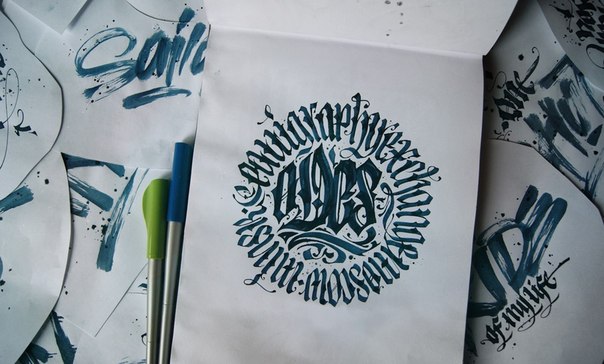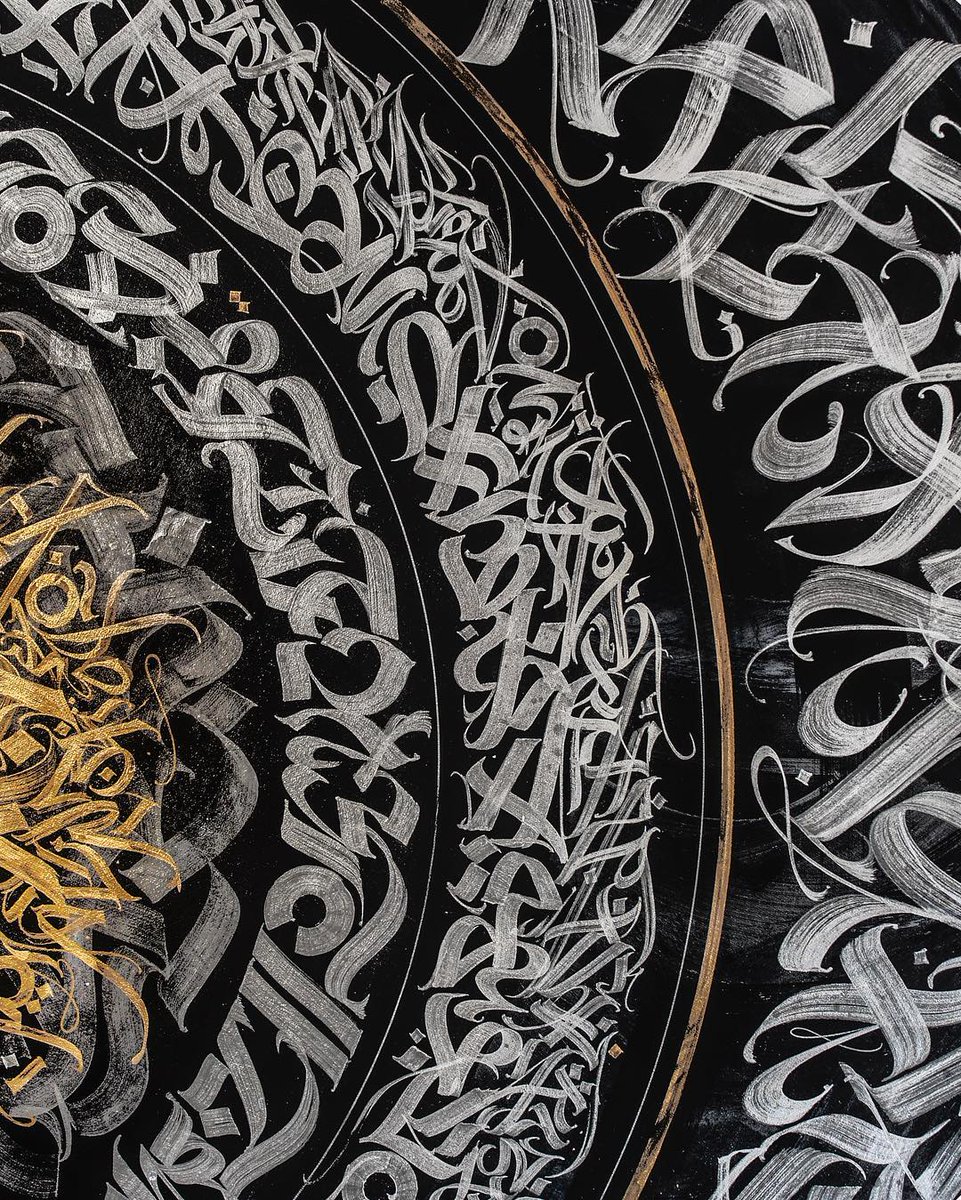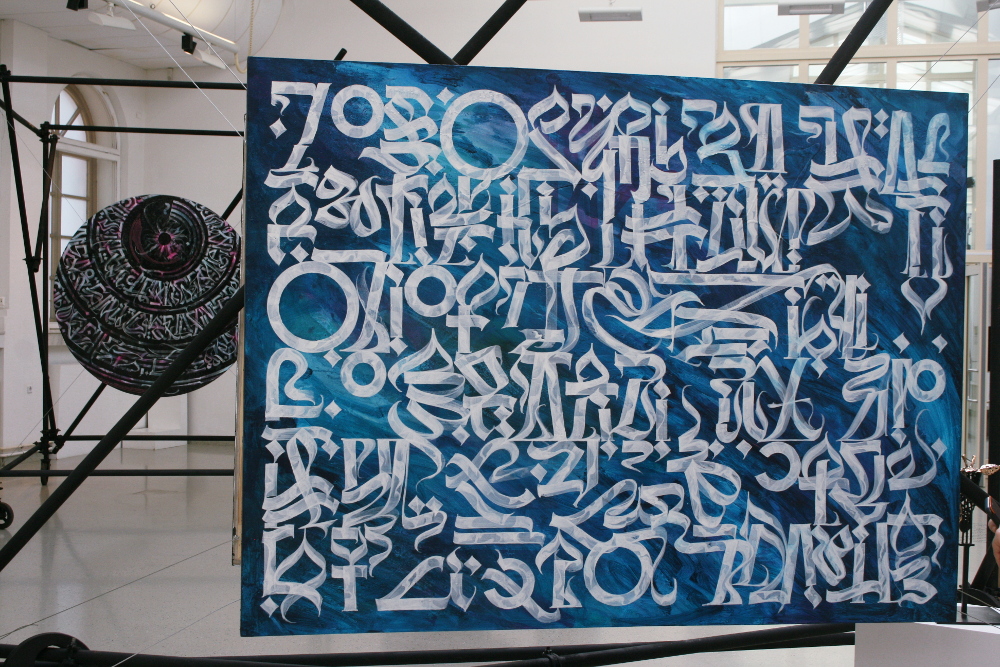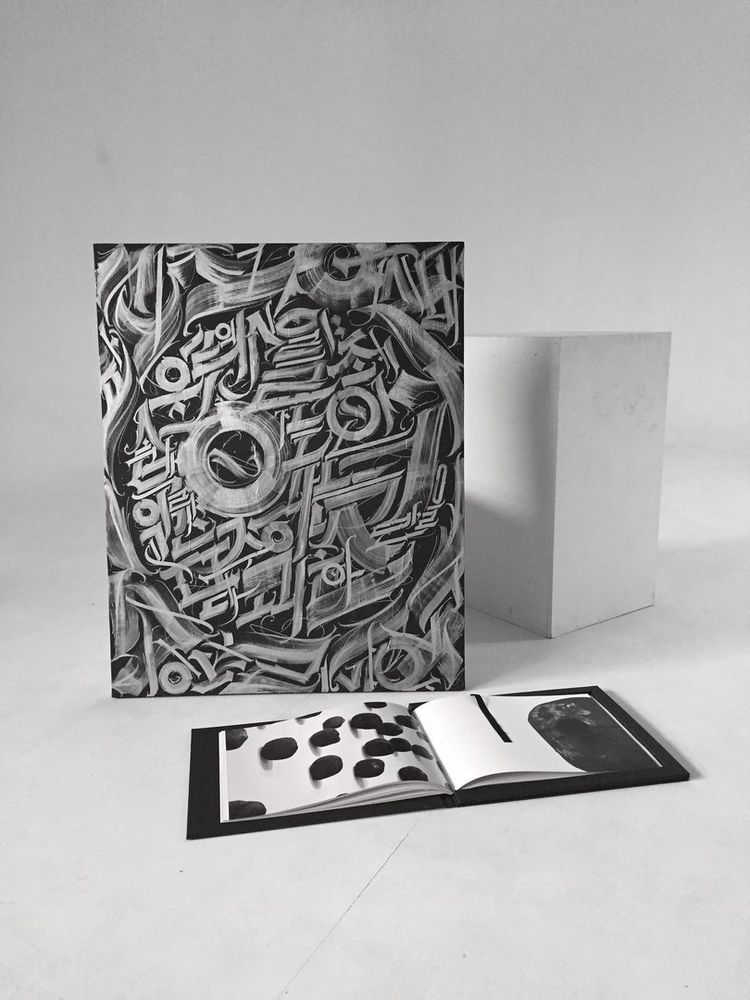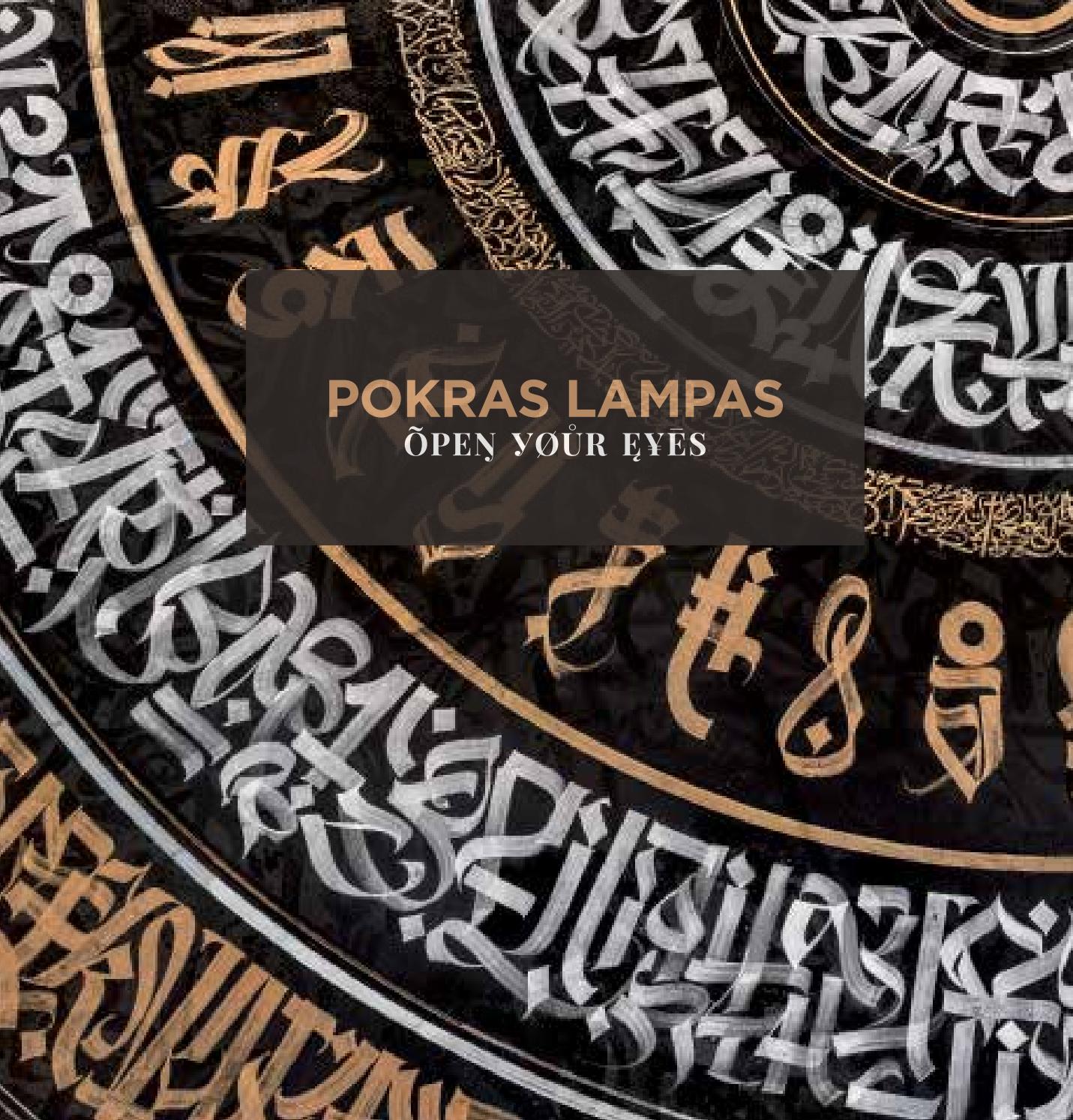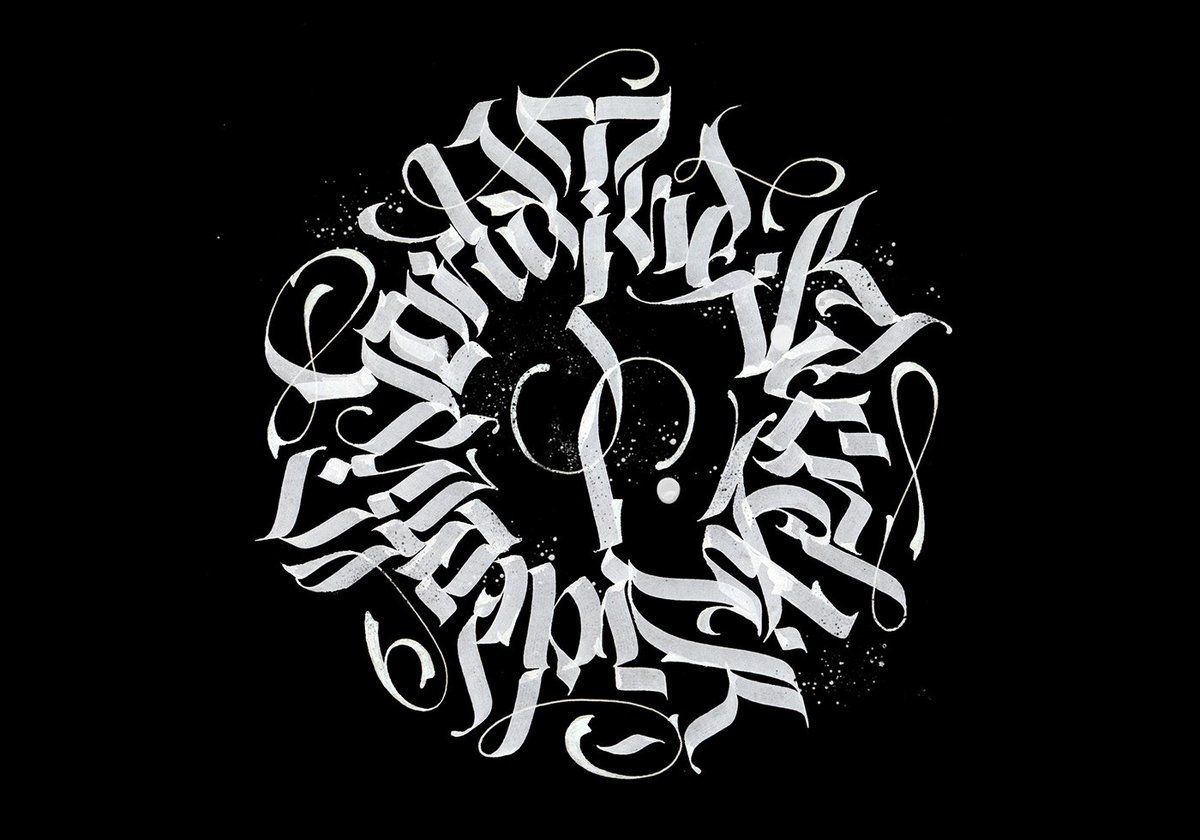
Лампас покрас шрифт: Покрас Лампас создал шрифт, вдохновленный Valorant | Valorant
Покрас Лампас создал уникальный шрифт для VALORANT
Российское подразделение Riot Games совместно с известным российским художником-каллиграфом Покрасом Лампасом объявила о творческой коллаборации. В рамках проекта Покрас Лампас создал уникальный наборный шрифт Г Ӆ Ѻ ƃ Å Л И Ʒ Å Џ И Я 1.0, вдохновленный популярным онлайн-шутером VALORANT.
В шрифте Г Ӆ Ѻ ƃ Å Л И Ʒ Å Џ И Я 1.0 Покрас Лампас объединил динамичную эстетику шутера VALORANT и собственный узнаваемый стиль. Локации, персонажи и механики игры послужили вдохновением для оригинальных элементов шрифта.
“Путешествуя по миру и осмысляя глобальные культуры, я транслирую свои знания и опыт через призму каллиграфического письма. Г Ӆ Ѻ ƃ Å Л И Ʒ Å Џ И Я — путь к единому знанию через транзитные формы письма, интегрированные каллиграфией будущего в мир через призму искусства.
VALORANT — прекрасный пример интеграции различных идентичностей, народов, стран и культур в рамках одного игрового мира, и именно поэтому мой первый наборный шрифт появляется в этой вселенной”. — заявил Покрас Лампас.
На первом этапе, который уже начался, участники смогут получить автоматически сгенерированный “Жетон агента” с их игровым никнеймом из VALORANT, написанным шрифтом Г Ӆ Ѻ ƃ Å Л И Ʒ Å Џ И Я 1.
0 от Покраса Лампаса.
«Чтобы создать что-то новое, нужно много экспериментов»
Современная каллиграфия глазами Покраса Лампаса
Если вы интересуетесь дизайном и современной каллиграфией, то наверняка вас можно было встретить 19-20 августа в «Пери Инновации». В течение двух дней известный российский дизайнер и каллиграф Покрас Лампас, он же Арсений, на территории бизнес-инкубатора провел два занятия — теоретическое и практическое.
В первый день художник рассказывал о тенденциях в современном искусстве и дизайне на примере различных авторских коммерческих и арт-проектов, ну а во второй уже на практике познакомил участников воркшопа с самыми популярными каллиграфическими инструментами и основами работы с ними для самостоятельной практики.
На протяжении 7 лет Покрас Лампас экспериментирует с возможностями шрифтов: как было написано на одном из российских порталов: «его стиль сочетает брутальность граффити с разнообразием используемых форм, цветов и инструментов, а также стремлением к большим масштабам».
Побывав на воркшопе мы смогли лично убедиться в таланте и масштабности работ Арсения. О том, как он начинал свой путь, какие вещи повлияли на становление его собственного стиля и что стоит ожидать в ближайшем будущем от самого популярного каллиграфа России, читайте в нашем интервью.
— То есть ты решил, что публика здесь не твоя?
— Ну, в общем-то да. Я считал, какой смысл рассказывать людям то, что им не интересно. Но в этот раз я получил приглашение от «Пери инновации», касающееся конкретного мастер-класса по каллиграфии, меня это в какой-то степени порадовало, значит, движение в этом направлении тут появилось.
— Нам рассказывали, что тебя даже попросили снять сережку в ухе.
— Да, есть такое дело (улыбается). Сказали, что реакция может не у всех быть положительная. Ну, я подумал и ладно, я всё-таки в гостях, можно и так.
— Я знаю, что у тебя есть много знакомых ребят из Кавказа, в частности из Дагестана.
— Да, у нас есть группа, где есть ребята из Дагестана — это Данил, Гаджи, Муслим. Вообще, мое общение с ними началось со знакомства с Данилом, у нас есть сообщество под названием «Десигн» про шутки о дизайне, где мы прикалываемся над незадачливыми клиентами и всё в таком роде. No Name, это ник Данила, всегда был одним из самых активных пользователей, с отличными шутками, и я даже не знал, что он из Махачкалы. Потом мы как-то пересеклись в Питере и стали дружить с ним в реальности. Ну а сегодня я уже сам у него в гостях.
— Давай поговорим о твоей работе, мы присутствовали на воркшопе, и в процессе общения с аудиторией ты упомянул, что у тебя нет художественного образования.
Taberna — это результат исследования тенденций в дизайне вывесок для баров, упаковки спиртных напитков и уличной одежды. Taberna — это забавный дисплейный шрифт с версией Sans, которая обеспечивает более чистый и простой дизайн, и шрифтом с засечками, который придает тексту более характерный и мрачный характер. Версия Script идеально сочетается с жирными заглавными буквами шрифта. Taberna — очень универсальный шрифт, который хорошо подходит для заголовков, плакатов, логотипов, вывесок и многого другого! »
Brushability (Любовь)